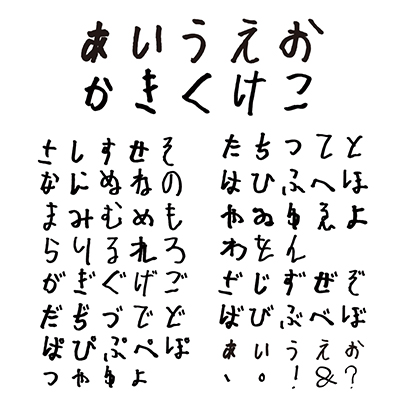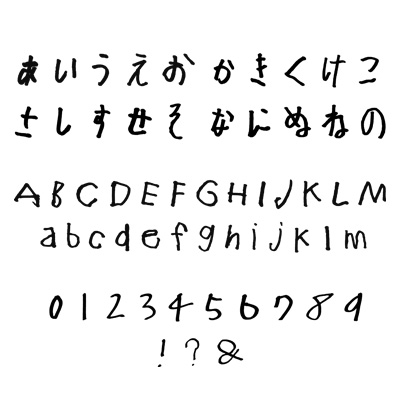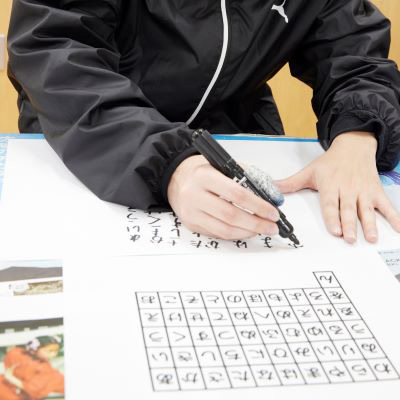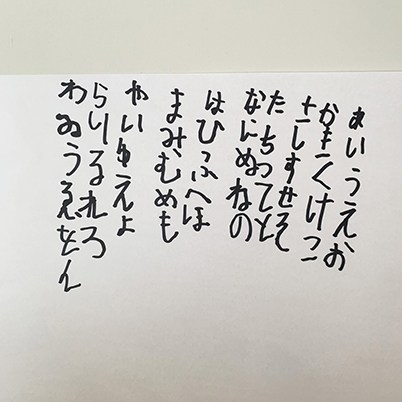
ビーズ王子の文字フォント
ビーズ王子の楽しいリズムと間合いを感じるかな文字
字を書きました(jo)
ビーズ王子ジョーさんの文字の動きや抑揚は、楽しいリズムを感じます。素敵な間合いや大小のバランスを出来るだけそのまま生かしました。(Tomomi Sakauchi)
ビーズ刺繡のブローチが大人気の作家です。鉛筆を指先で優しくそっと持って、真剣に書きました。(玉川福祉作業所)